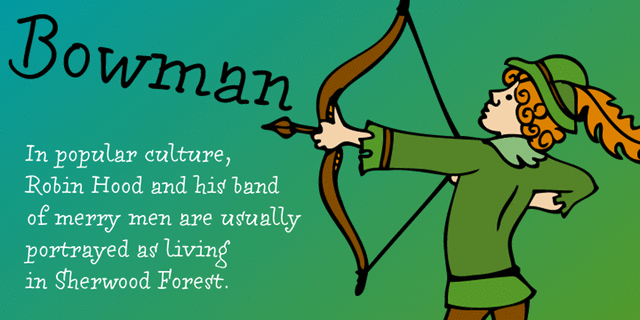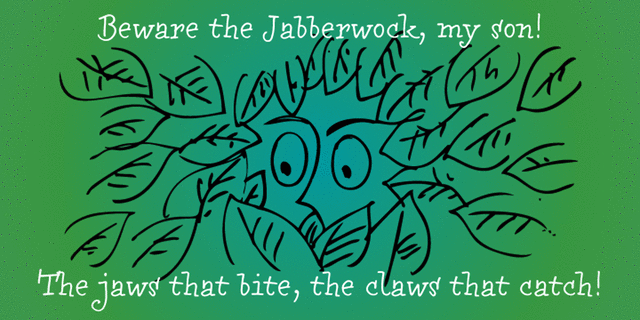
About BowmanШрифт Bowman (Лучник) — акцидентный брусковый шрифт, написанный вручную маркером. Благодаря живому и подвижному характеру его можно использовать в комиксах, иллюстрациях и других местах, требующих неформального подхода. Дизайнер Александра Королькова. Выпущен компанией ПараТайп в 2010 году.
Associations for font family BowmanTypeface personality and character:
dashing, daring, informal, playful, cheerful, restless, emotional, naughty, mischievous, agile, interesting, freewheeling, free, youth, risky, quarrelsome, provocative, vigorous, distinctive, affable, children, naive, alive, temperamental, motivating, active, cartoonish, summer, quick, sweeping
tale, camp, toy, game, notebook, stationery, pencils, markers, plasticine, handmade, children's book, adventures, animation, zoo, pet shop, animals, recreation, school, diary, Cartoon, graphics, illustration, pupil, schoolboy, morning Typeface associated with age: